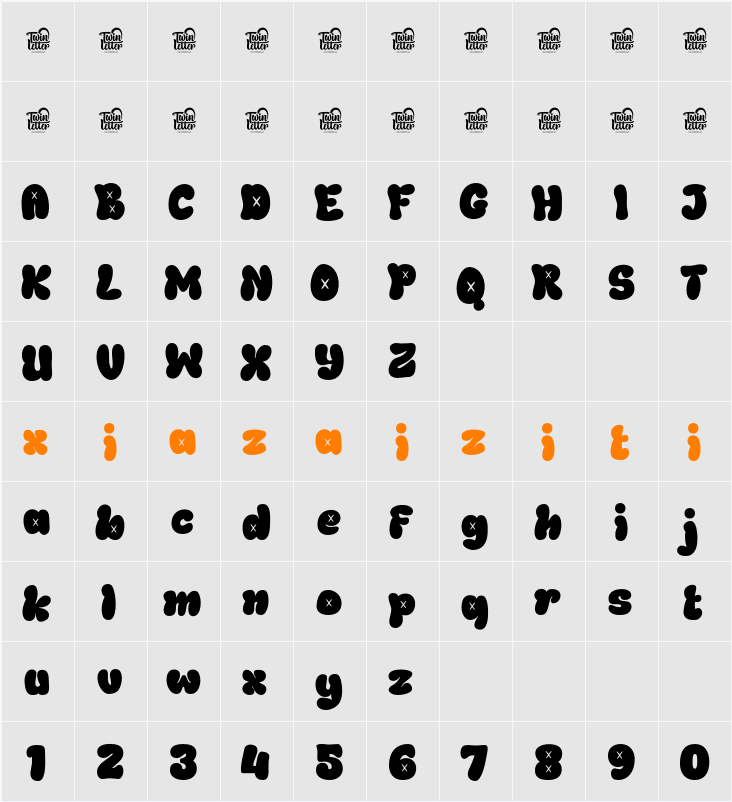
XERULAH Trial
XERULAH Trial,这款字体结构工整、笔画清晰,兼顾美观与易读性,适用于标题、正文、海报、包装、LOGO 等多种场景。字形优雅稳定,风格百搭耐看,适配日常排版与创意设计,让文字呈现更舒适、更具质感。XERULAH Trial一笔一画,皆是细节,以均衡的比例、流畅的线条打造舒适视觉体验,字形端正大气,风格简约现代。无论是商业设计、品牌宣传还是日常排版,都能轻松驾驭,让文字更有格调与力量。XERULAH Trial字体下载。
• 制造商: twinletter
• 设计师: Andika